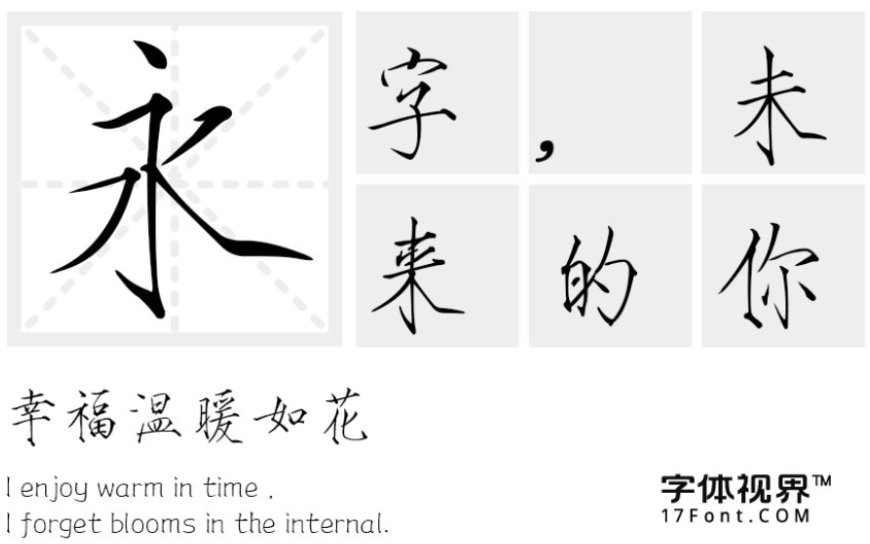
三极瘦金简体发布
字体名称:三极瘦金简体
字体类别: 书法字体、黑体
适用场景:广告 产品包装
三极瘦金简体简介:三极瘦金简体源自宋徽宗书法字体。这款字体的笔画纵横飘逸,狭瘦挺拔。横画收笔带钩,竖画收笔带点。整个字面狭长,中宫偏小,重心稳定。适用商业类广告和产品包装设计及店面设计。
三极瘦金简体预览图展示: